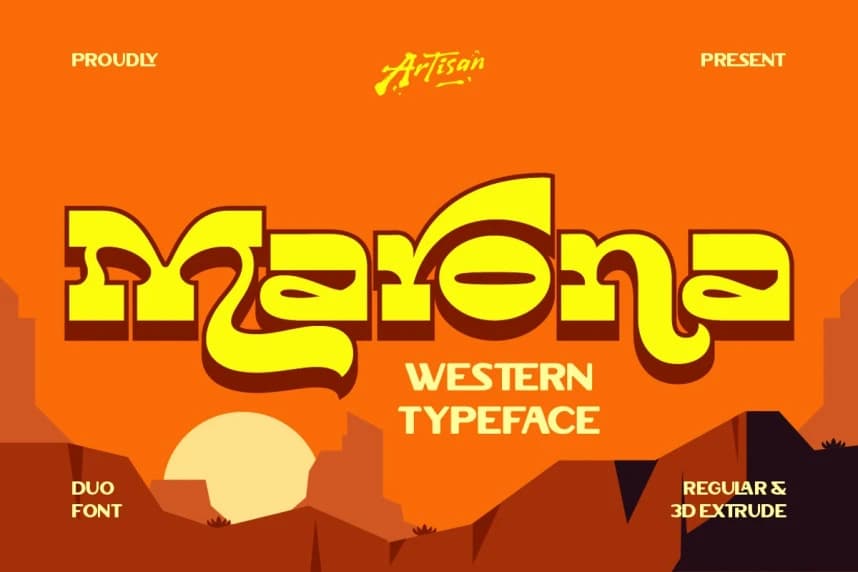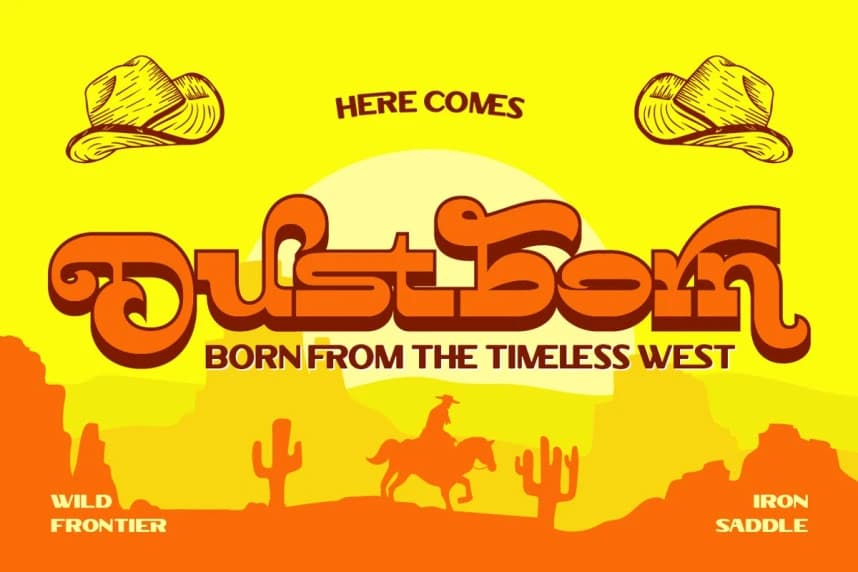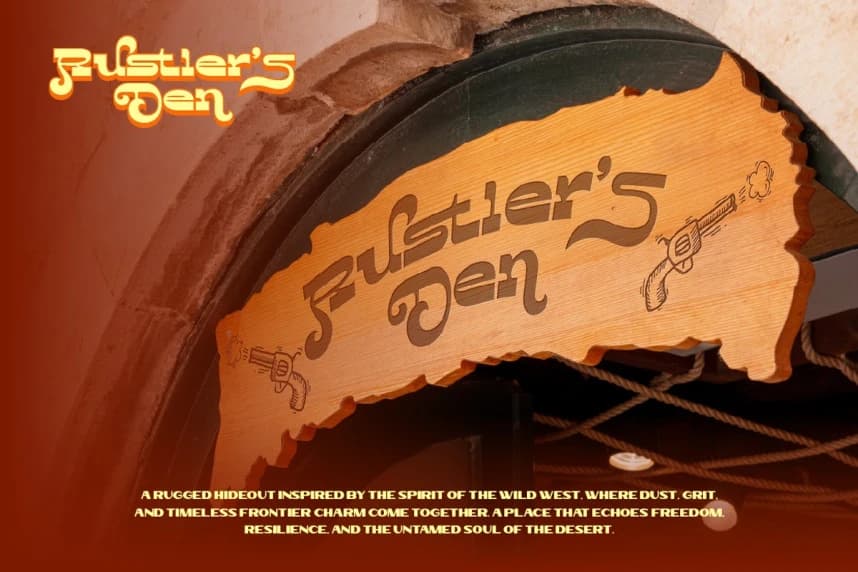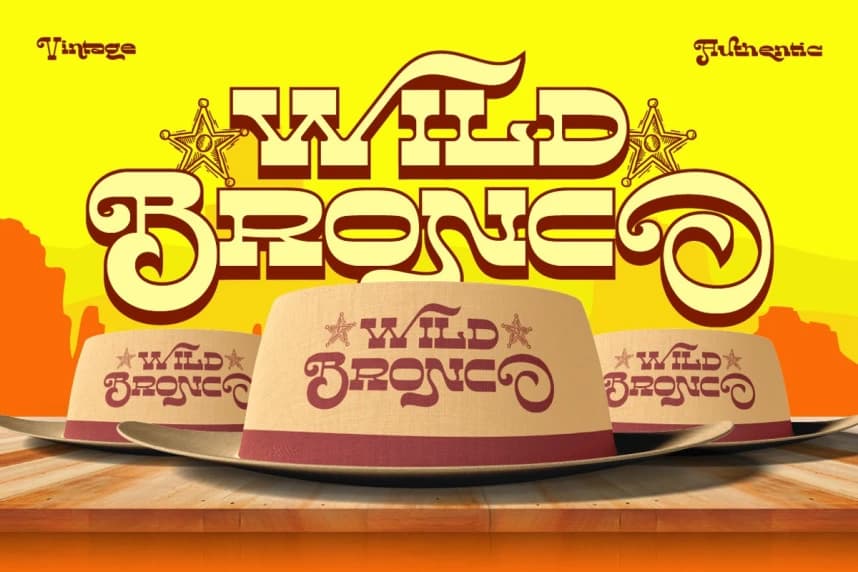
Marona Font, modern ve eğlenceli bir dokunuşa sahip, Batı esintili cesur bir yazı tipidir. Kalın yuvarlak hatları ve benzersiz harf biçimleri eğlenceli ama güçlü bir hava verir; bu da logolar, afişler, başlıklar veya öne çıkması gereken herhangi bir şey için mükemmeldir.
Marona Font, kalın batı esintili bir tipografidir ve modern, oyunbaz bir dokunuşa sahiptir. Kalın eğrileri ve özgün harf biçimleri eğlenceli ama güçlü bir hava yayıyor, bu da logolar, posterler, başlıklar veya öne çıkması gereken her şey için mükemmel hale getirir.